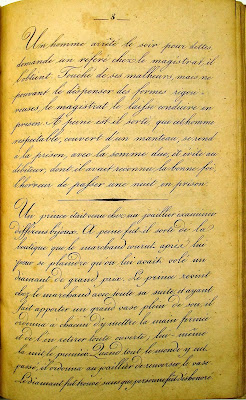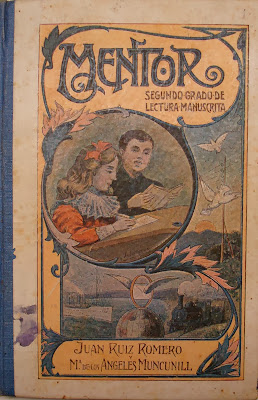
Este artículo lo centraré básicamente en algunos libros para aprender a leer y escribir desde principios del s. XIX hasta la década del los años sesenta del siglo XX. Una de las primeras tareas que debían aprender los alumnos era poder leer y escribir y después a contar, en estas tres tareas se describe lo mas elemental de las asignaturas que conformaban el aprendizaje en las escuelas de primarias, aunque en algún que otro artículo en este blog me he referido a estos temas, silabarios, abecedarios etc.. para niños, en el presente voy presentaros una serie de libros básicamente pensados para que los alumnos pudieran leer un sinfín de diferentes caligrafías, después veremos lo que eran los cuadernos de caligrafía y finalmente os mostraré algún que otro trabajo caligráfico de esta época.
Todas estas muestras son aleatorias y no representan ni mucho menos el total de la multitud de libros y cuadernos de este tema, ya que la mayoría se editaban por provincias o incluso por escuelas, pero nos darán una imagen curiosa de como ha cambiado en un centenar de años la educación de los niños. En mercadillos de viejo o librerías anticuarias seguro que podéis adquirirlos por muy poco dinero o mirando en el desván seguro que aparecen si no estos otros similares.
LIBROS DE LECTURA, PARA LEER DIFERENTES SUERTES DE LETRA MANUSCRITA
Gracias al procedimiento de la invención de la litografía en Europa se empezó a principios del s XIX a introducir libros para poder aprender a leer muestras manuscritas se llamaban libros autografiados.
I- El primer libro del que dispongo es un libro francés titlulado: "Recueil de Fac-simile de toutes espèces d'écritures, Françaises et Anglaises & pour exercer a la lecture des manuscrits et des écritures difficiles". Strasbourg: A la litographie de F.G. Levrault, 1832. sin Autor. 8º, 84 páginas, encuadernación en cartoné de época.
Después de unas muestras de textos caligráficos, introduce ya muchos tipos de letras diferentes y al final una pequeña sección de documentos históricos.
II- El primer libro publicado en España con este procedimiento de autografiado fue: "Miscelánea de Lectura de la letra Bastarda Española para el uso de los niños, escrita y autografiada" que escribió José Francisco de Azpiazu el 1844 y del cual podéis ampliar información en el pasado artículo de este blog: "La Caligrafía Española en el s. XIX, I Parte"
Este libro nos muestra una parte dedicada a la lectura y muestras de letras autografiadas y otra parte dedicada a las matemáticas y el comercio. Aunque su fin es enseñar no sería un ejemplo de manual didáctico para niños pequeños sino pensado para personas mas mayores que quieran aprender el arte del comercio y nociones sobre la historia y uso de la caligrafía y su lectura.
III- El "Arte Epistolar para facilitar la lectura de los manuscritos á los niños y adultos" escrito por Estéban Paluzie y Cantalozella en 1845. Editado en Barcelona por el mismo autor y como el anterior totalmente autografiado.
Este libro está indicado para aprender a leer muestras de caligrafías de diferente dificultad ya que según el autor los alumnos que ya saben leer muchas veces no consiguen leer letra manuscrita de trazo singular. Contiene 160 muestras de diferentes textos manuscritos algunos de una letra realmente endiablada.
La razón de citar estos dos libros es por la idea que seguirá vigente durante todo el siglo XIX y parte del XX que es imprescindibles que los niños aprendan a leer letra manuscrita a la vez que la tipográfica ya que el hecho de poder leer cartas, inscripciones y documentos era imprescindible para poder ser un ciudadano bien instruido. Veremos que en los libros que siguen esta máxima esta presente en todos ellos.
IV- Silva, Carlos
"D. Paleographo em escala Calligraphica para apprender a Leitura Manuscripta"
Lisboa: Instituto Calligraphico, 1883. 8º, 94 páginas
Este libro portugués es una edición similar a los anteriores en contenido e idea.Contiene diversos alfabetos y ejemplos de cartas familiares y de comercio.
V- Balmaña y Ros, Antonio
"Primer Libro de Lectura manuscrita para el uso de las escuelas elementales y de párvulos,
por D. Antonio Balmaña y Ros, caballero de la Real orden de Isabel la Catolica, Maestor de enseñanza superior y titular de la escuela elemental modelo de Espolla"
Barcelona: Vilás y grabado por Lit. Serra Jovellanos, 1898, 17ª edición.
8º, VI páginas en romanos, que incluyen: portada, retrato, dedicatoria y un pequeño prólogo + 74 páginas
Existen ediciones hasta hasta bien entrado el s. XX (1930)
Empieza este libro por unos abecedarios de diferentes estilos caligráficos y sigue con ejemplos de múltiples escritos con diferentes suerte de letras, incluye una sección de abreviaturas corrientes y después diversos documentos como cartas, pagarés, facturas etc...
VI- Martinez Aguiló, José
"Manuscrito Moderno. Consta de cinco secciones, á saber: Parte Literaria, Sección epistolar, Colección de autógrafos, Parte comercial y Sección poética..."
8º, Barcelona: L. Robert Impresor, 5ª edición, 1905. 192 páginas.
(Esta obra tuvo una distribución en muchas capitales de España y también en la Habana, Manila, Buenos Aires y Lima.) No encuentro ejemplares posteriores a esta fecha.